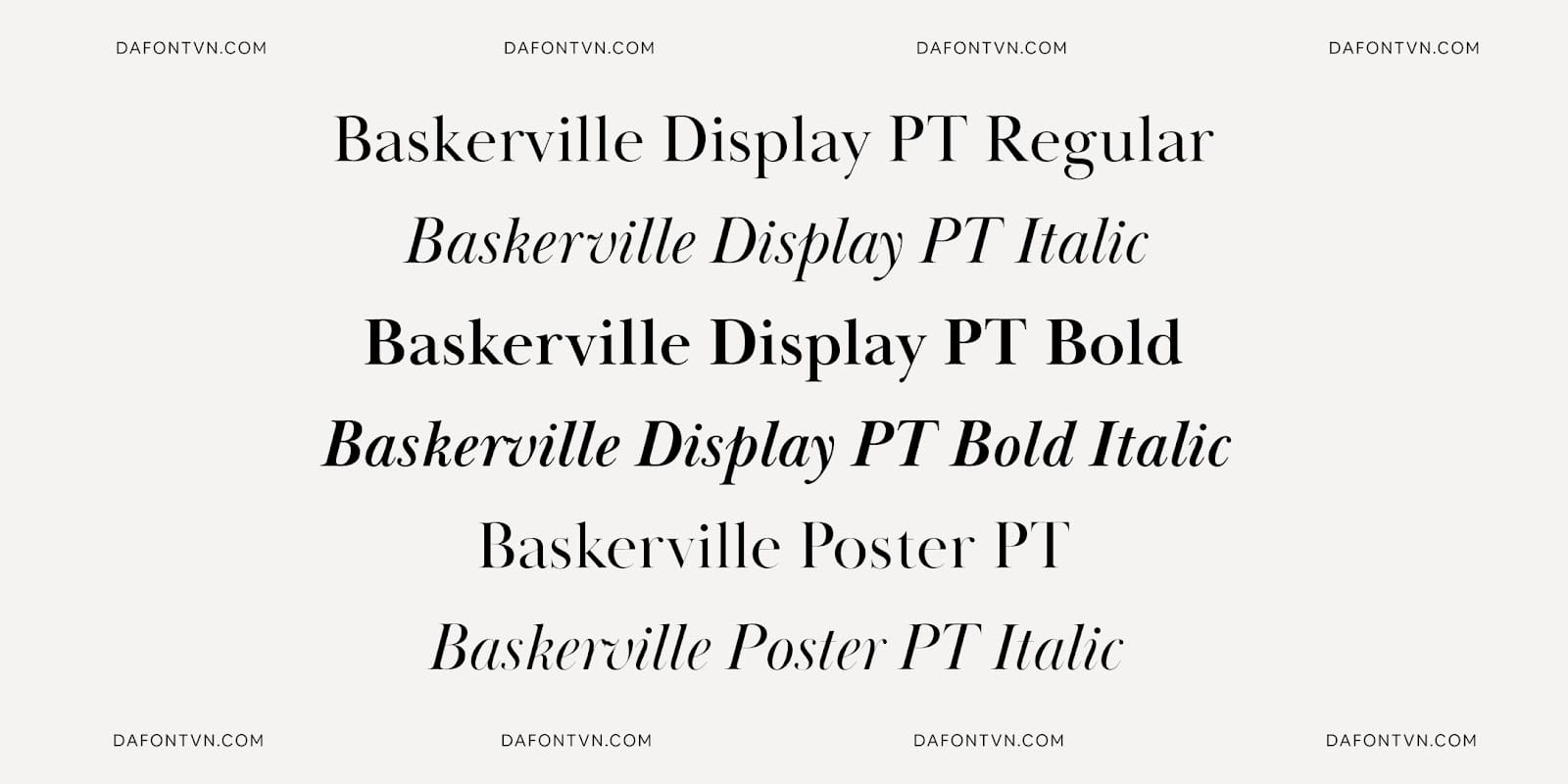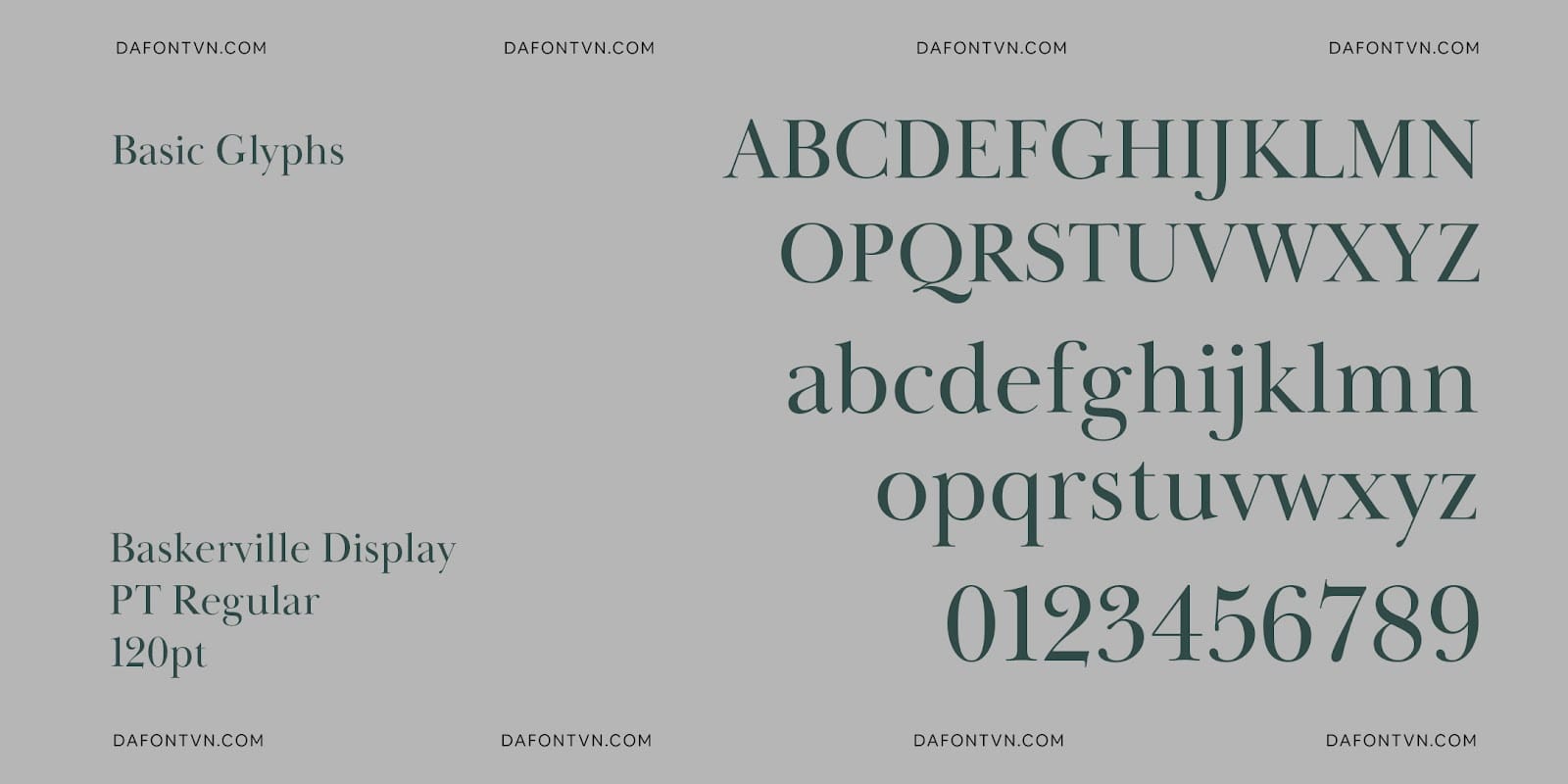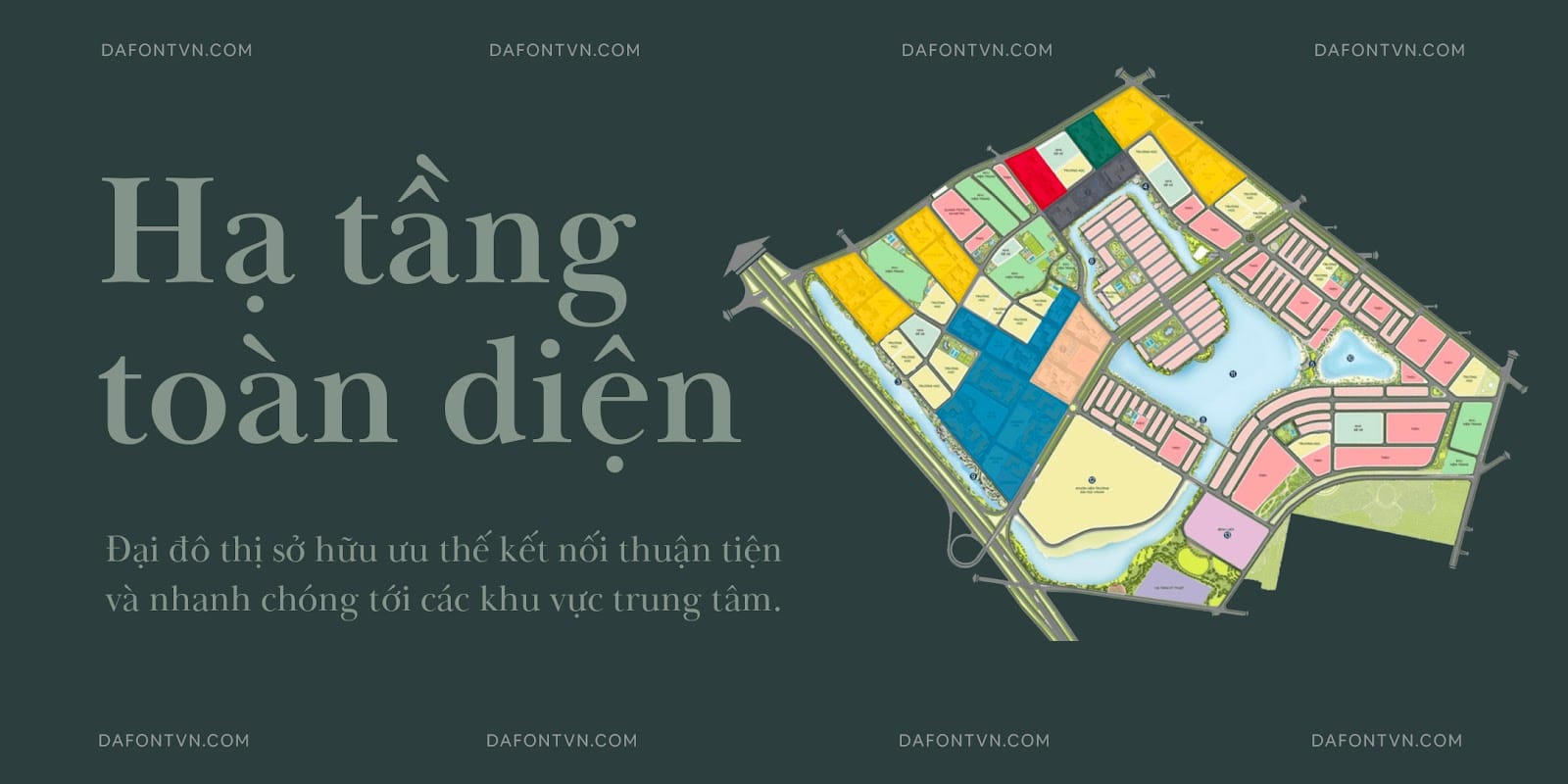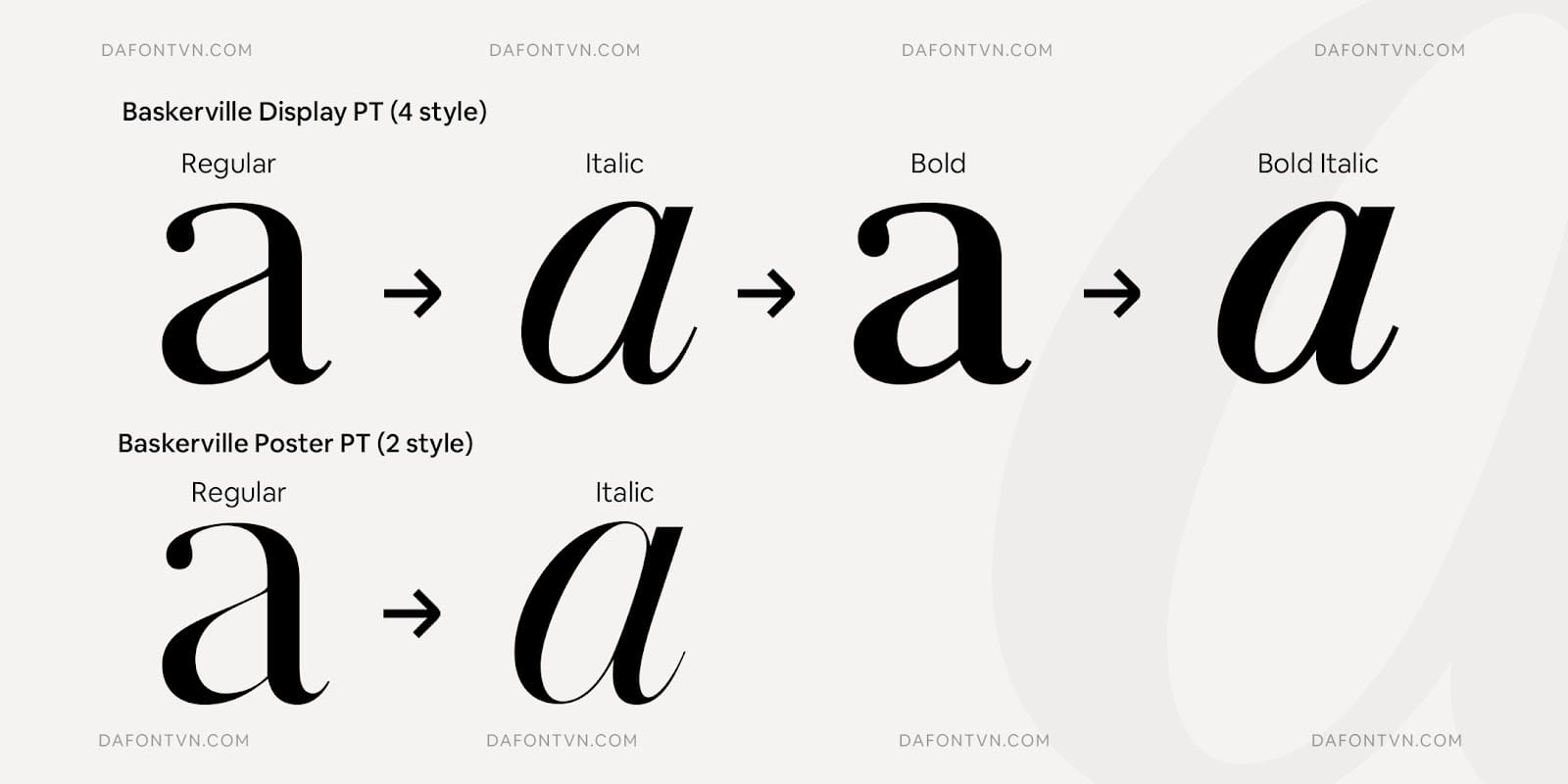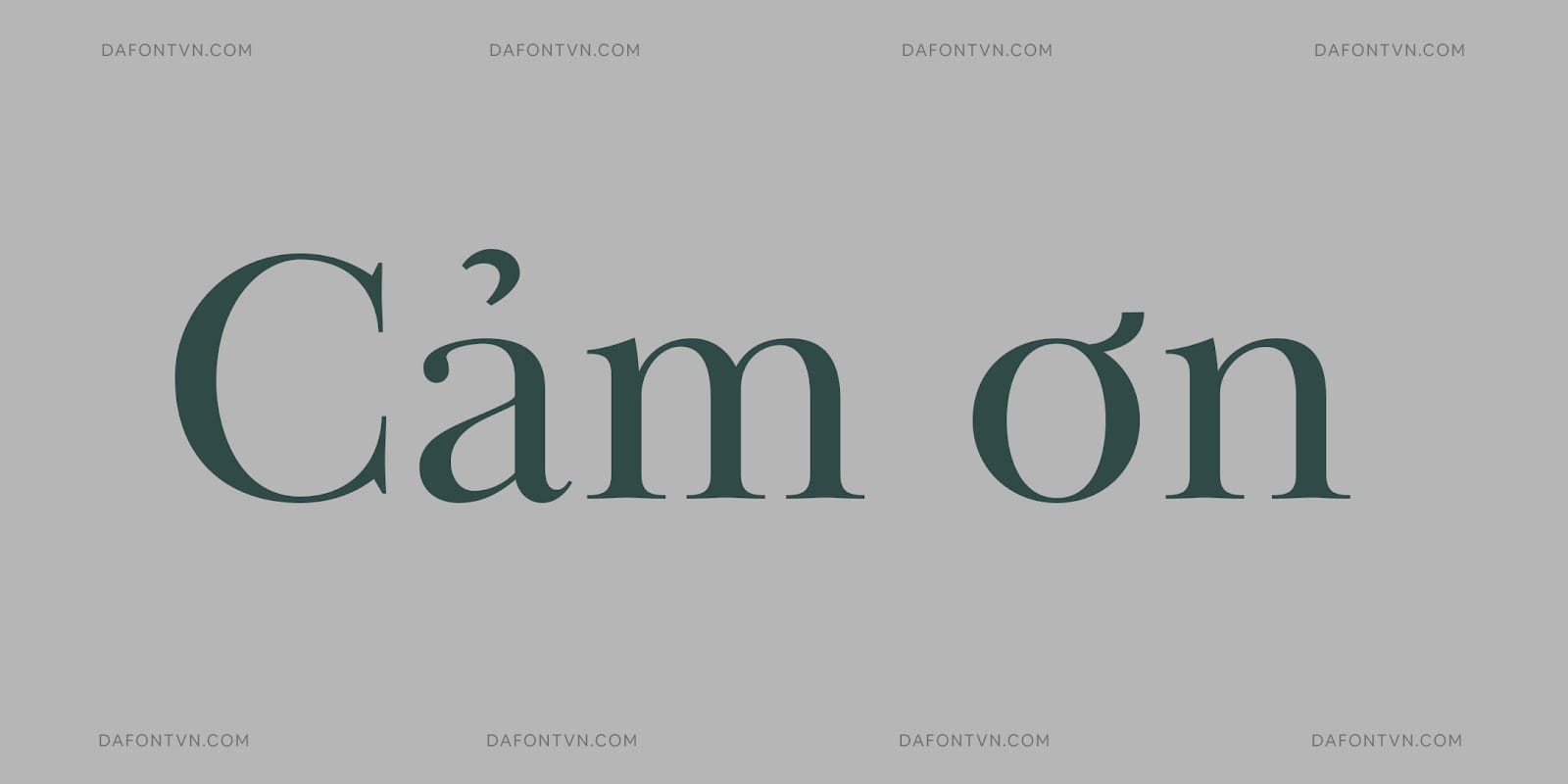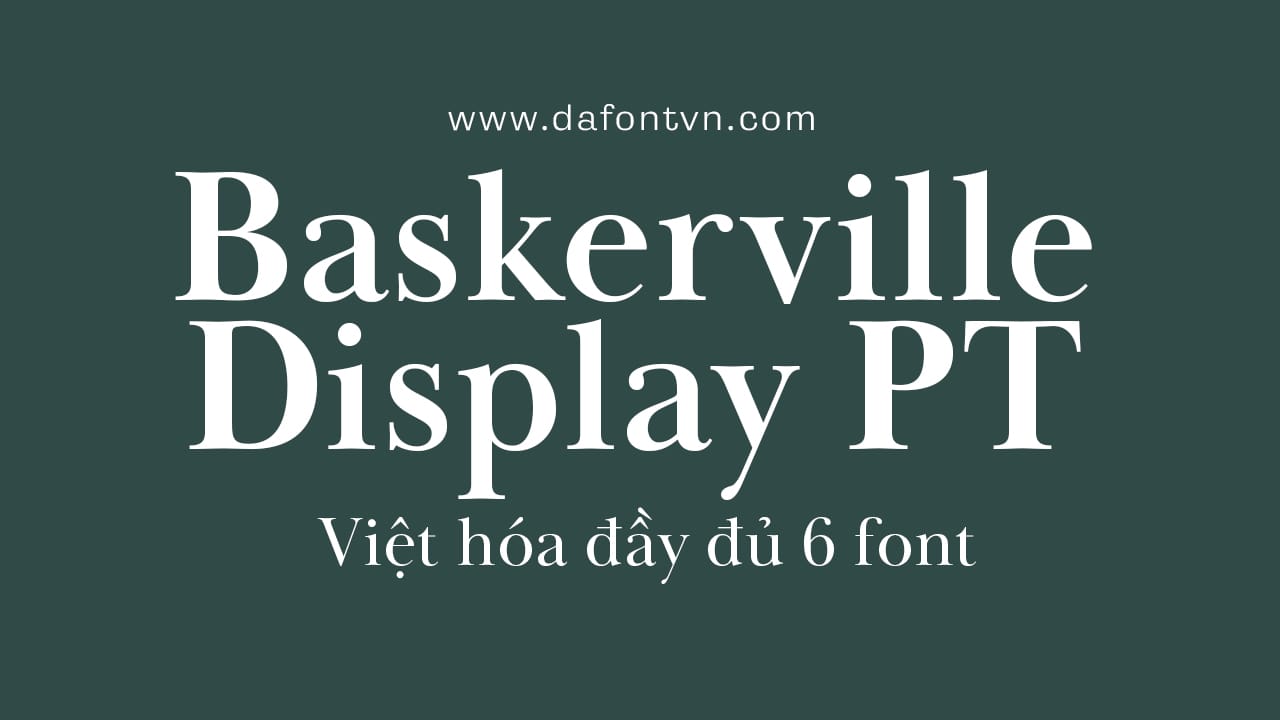
Baskerville Display PT là phông chữ hiển thị được lấy cảm hứng từ những kiểu chữ của John Baskerville và được thiết kế cho việc trình bày chữ hiển thị hoàn hảo và ấn tượng.
Hai trọng lượng của Baskerville Display kèm theo phiên bản nghiêng phù hợp nhẹ hơn rất nhiều so với các phiên bản chữ văn bản hiện có của Baskerville. Một bổ sung tốt cho bộ phông này là Baskerville Poster, phông chữ này sẽ trông rất ấn tượng ở cỡ rất lớn.
Bộ font này phù hợp cho các dự án thiết kế cần sử dụng một kiểu chữ hiển thị chất lượng như dự án bất động sản, tiêu đề, poster, quảng cáo…
Bộ font việt hóa bao gồm 6 kiểu:
- Baskerville Display PT Regular
- Baskerville Display PT Italic
- Baskerville Display PT Bold
- Baskerville Display PT Bold Italic
- Baskerville Display PT Poster
- Baskerville Display PT Poster Italic